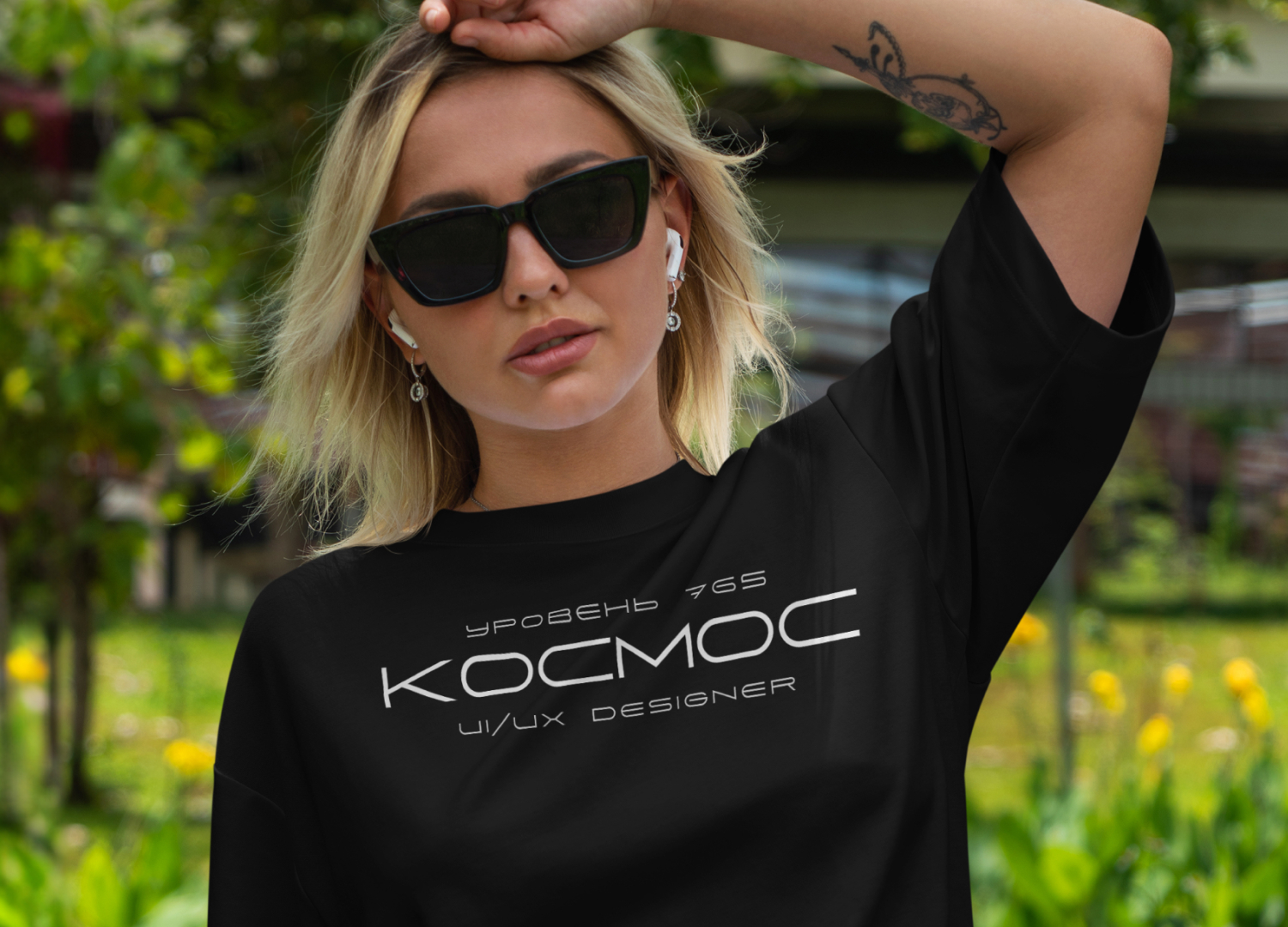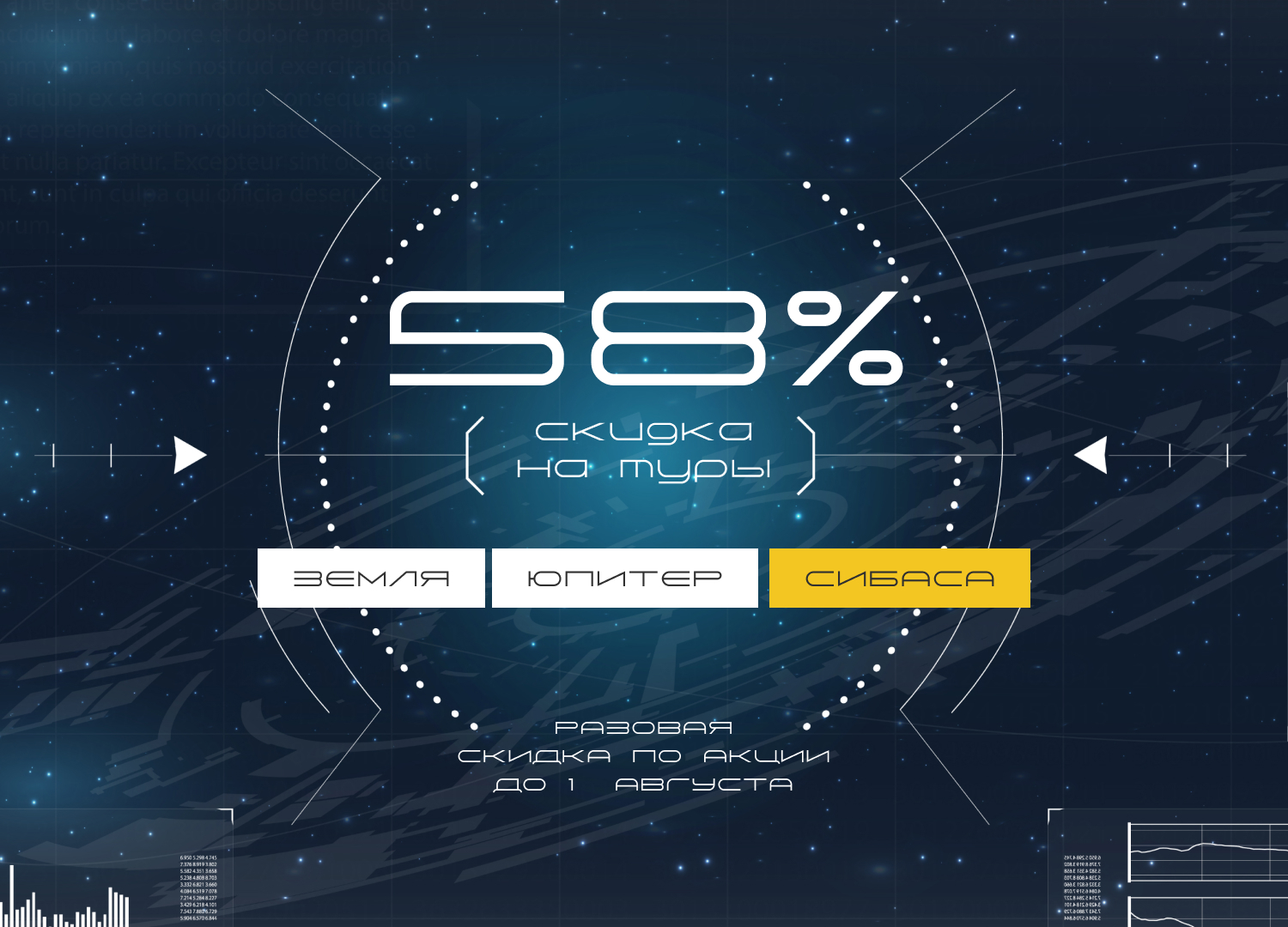
Бесплатный космический шрифт
Лови новый шрифтец) Project Space. Космический, футуристичный шрифт с поддержкой кириллицы. А главное полностью бесплатный для всего. Для объемного текста подходит не оч. А вот в коротких заголовках вполне.